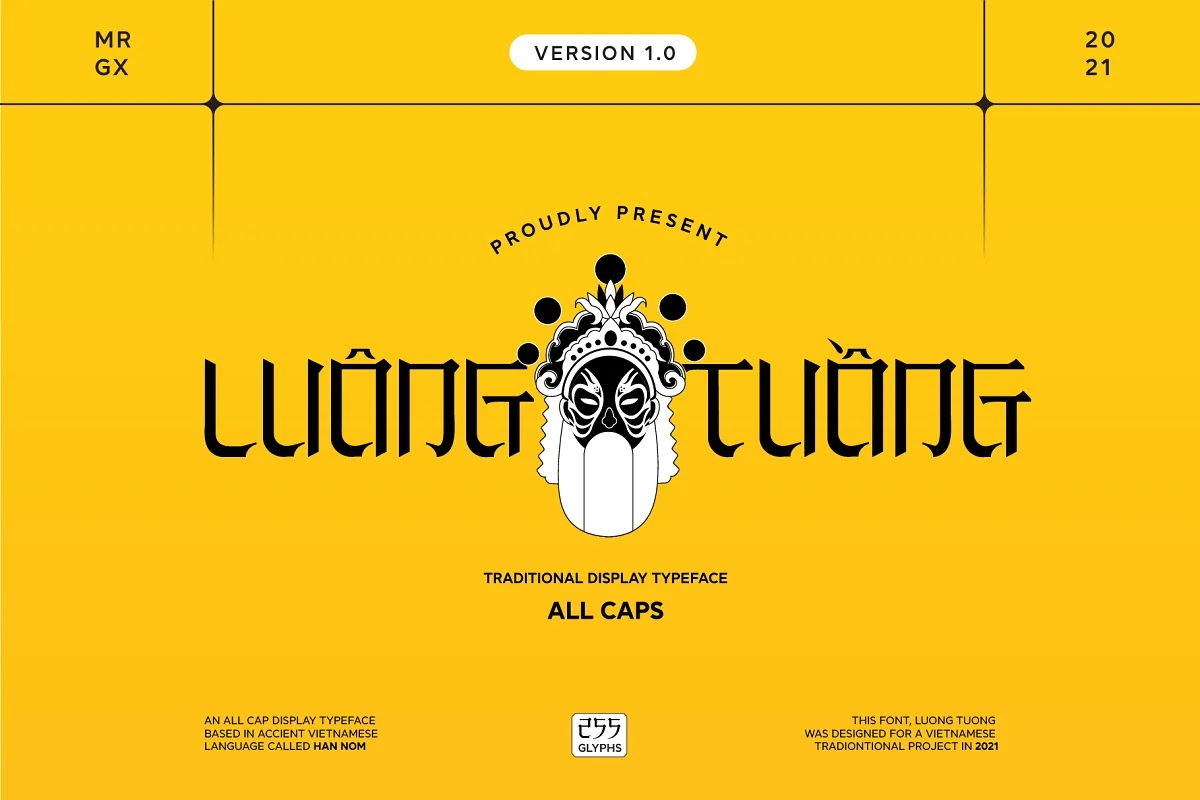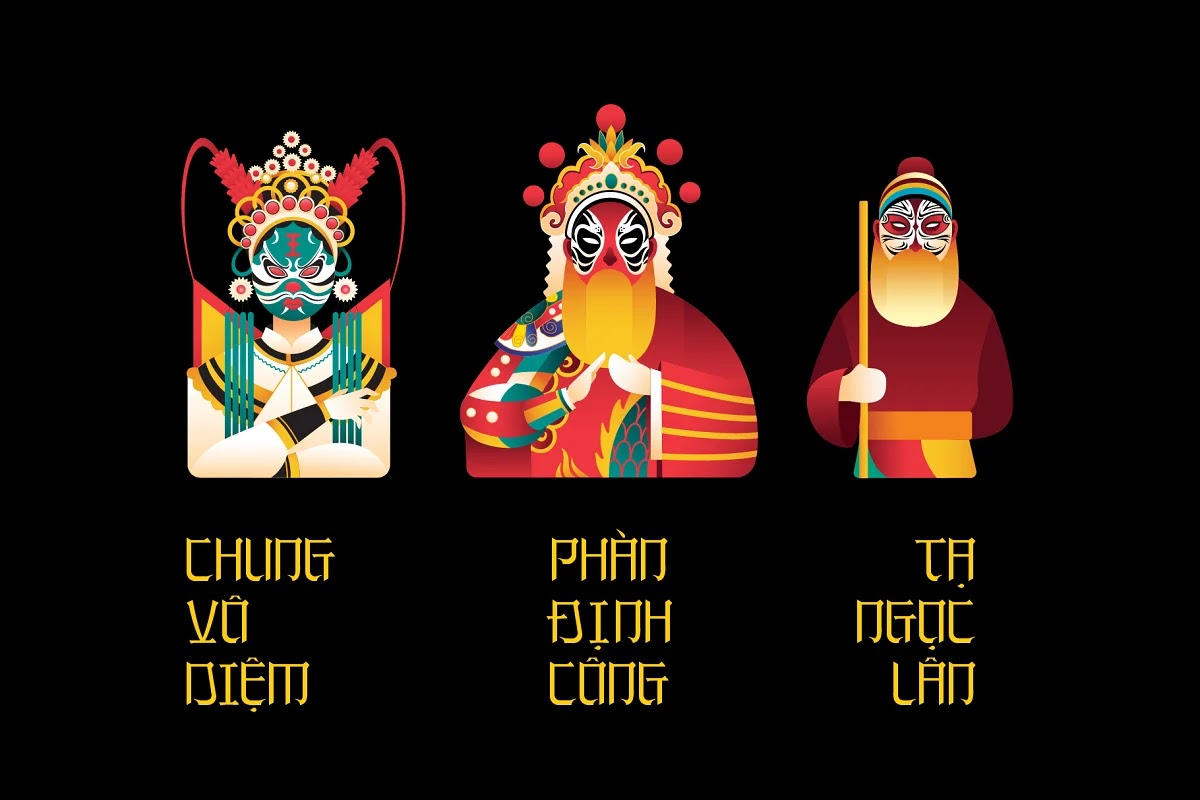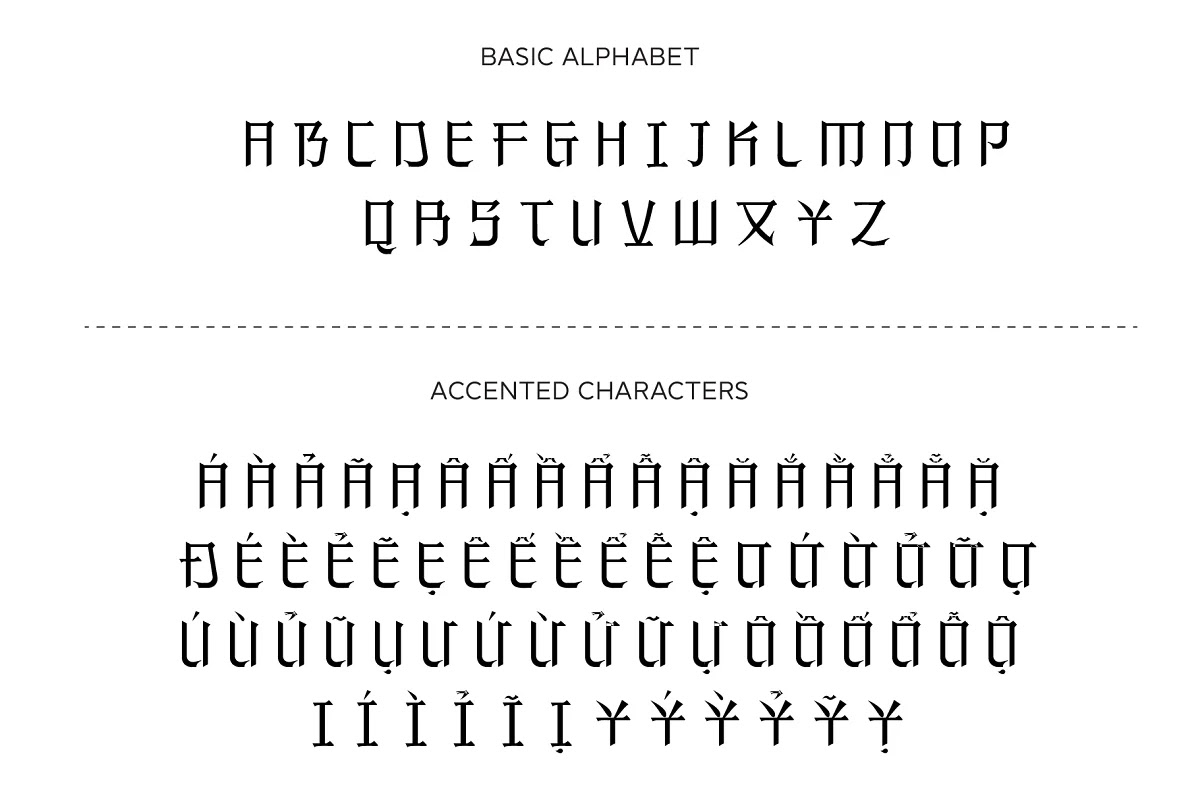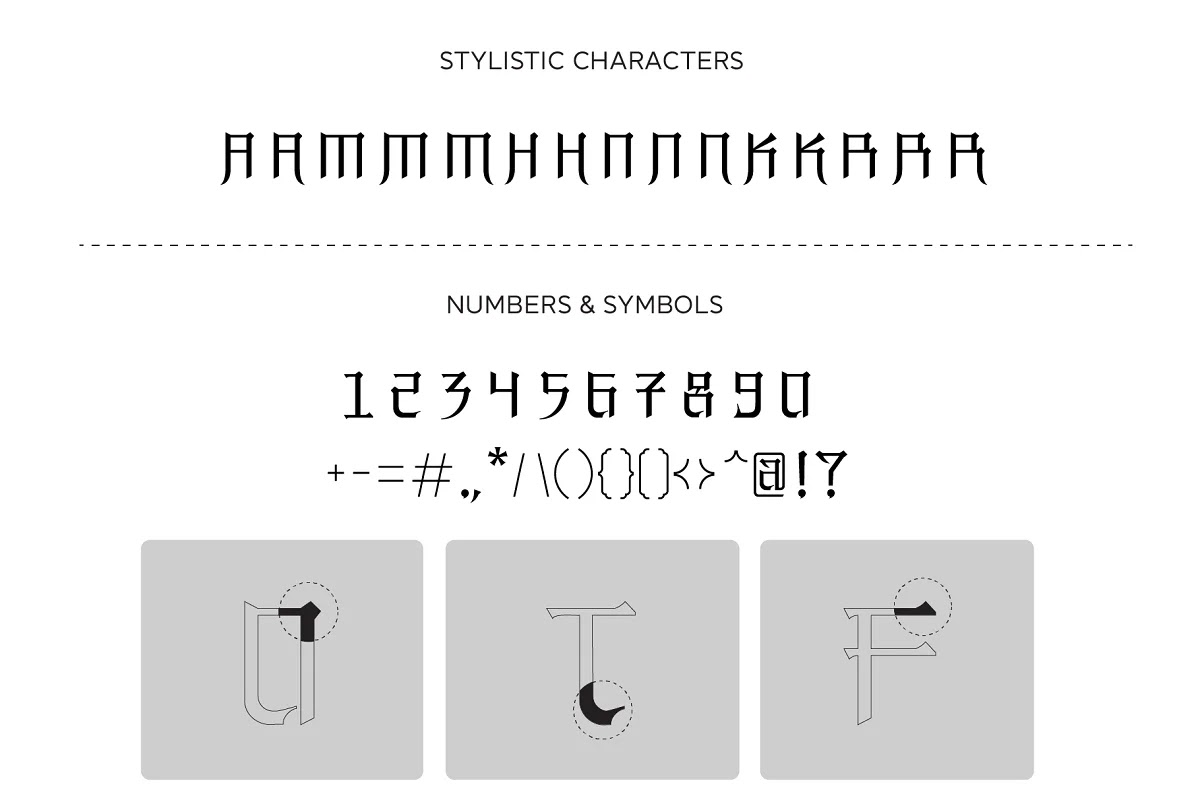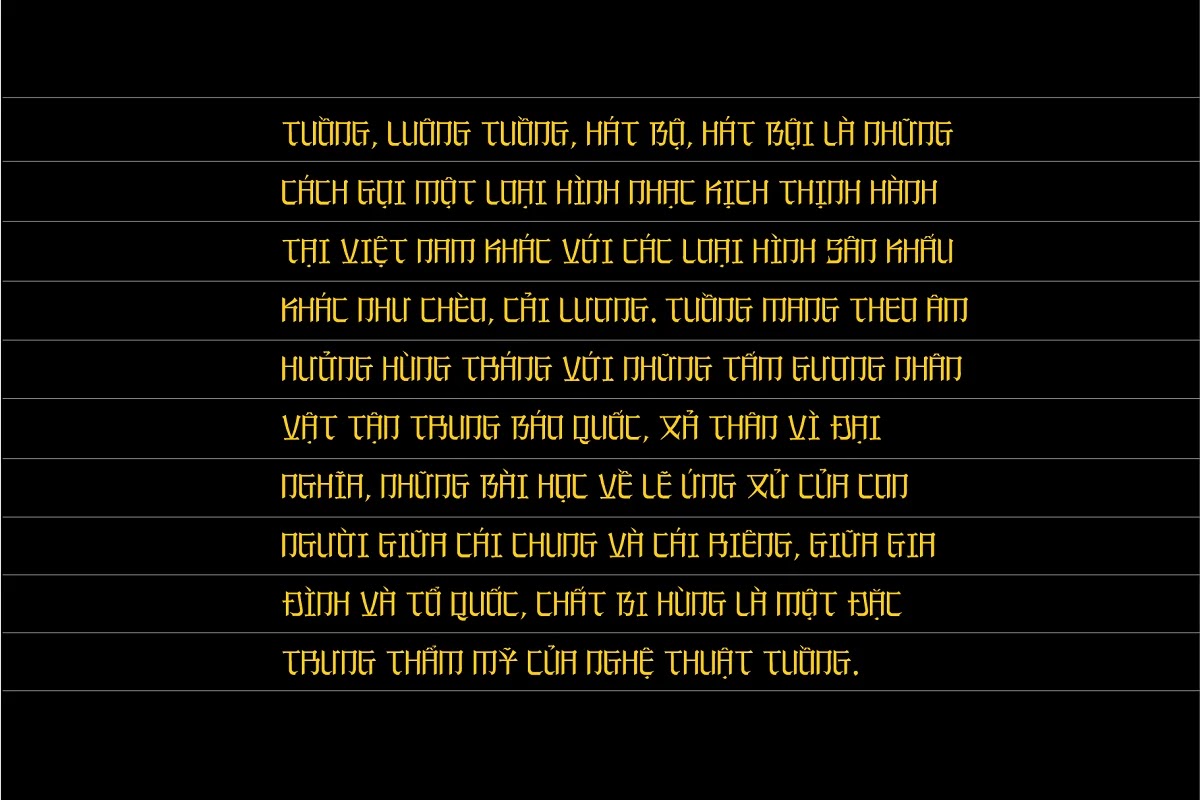
Font LuongTuong Typeface – Vietnamese Display Typeface
LUONG TUONG là một font chữ tiếng Việt thông dụng là Hán Nôm được thiết kế bởi Trung Dung. Typeface này là 1 phần nhỏ trong project Tuồng của Dũng. Một font khá ấn tượng. Kiểu chữ này là tuyệt vời cho dự án văn hóa truyền thống!